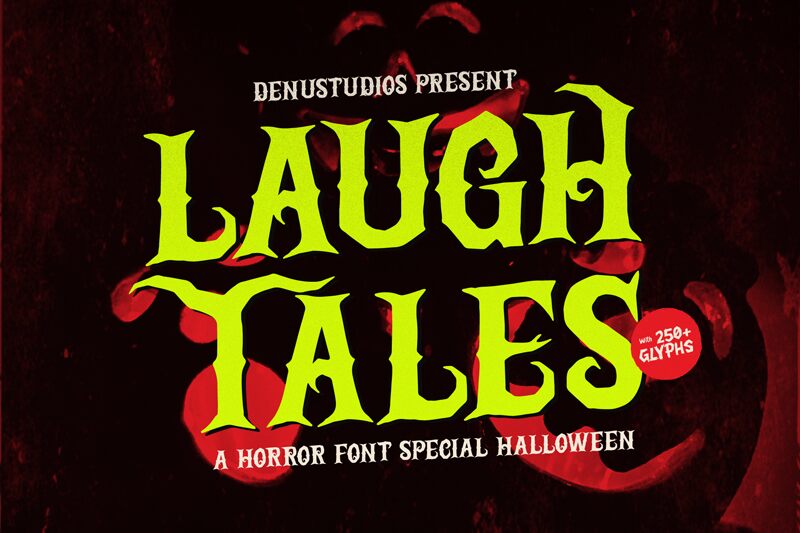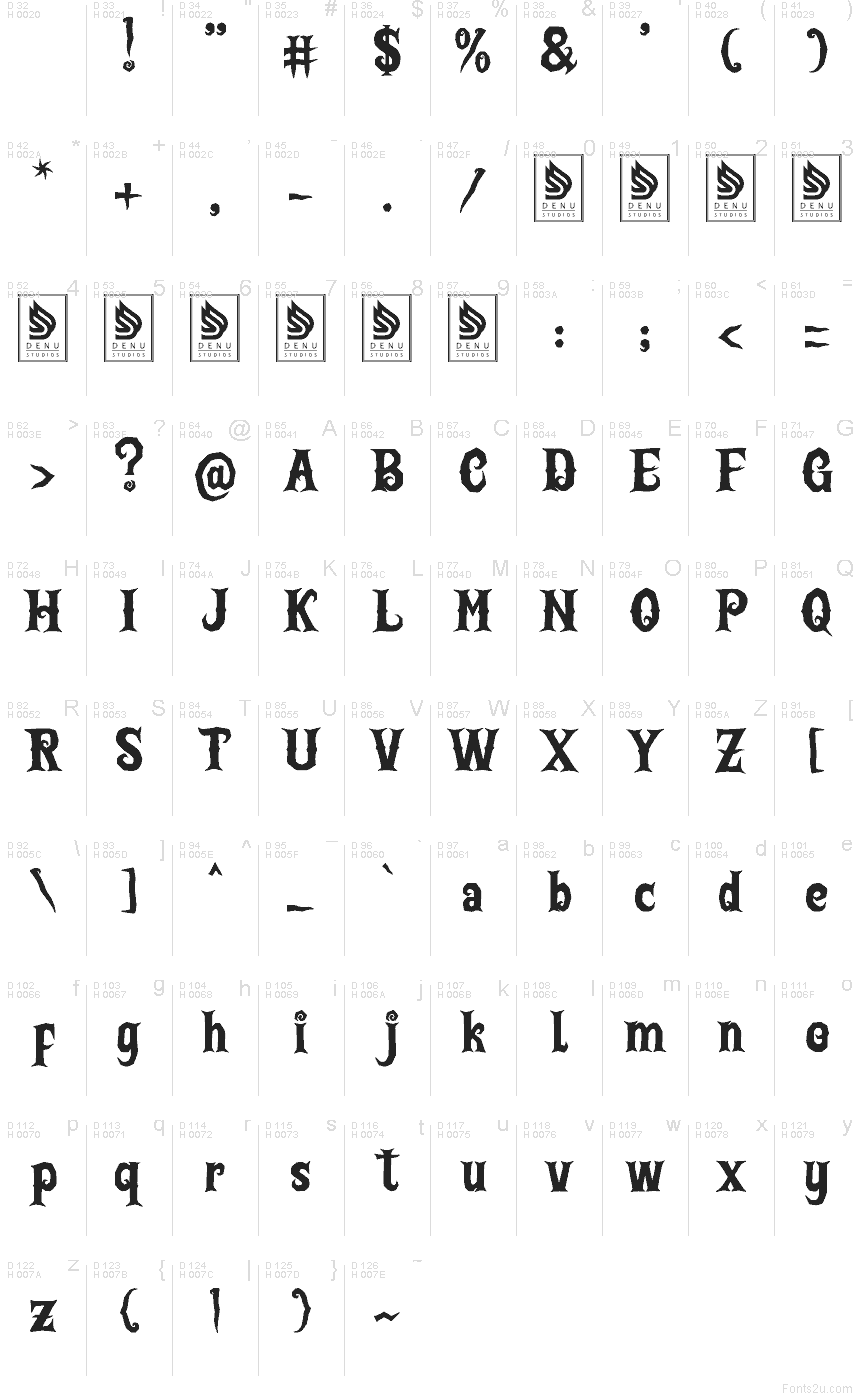
Laugh Tales de Denustudios es una tipografía Blackletter gratuita para Halloween con un aire gótico de cuento. Sus letras se definen por puntas afiladas y cornudas junto con formas medievales robustas, pero las curvas exageradas y los finales en gancho le aportan un toque divertido en lugar de solemne, dándole esa sensación traviesa de fogata.
Encaja perfectamente en carteles de eventos de terror, portadas de libros espeluznantes, embalajes temáticos, invitaciones a fiestas y títulos cortos estilo logotipo que requieren una fuente gratuita con un punto de folklore y amenaza. Gracias a que sus formas son compactas pero dramáticas, funciona especialmente bien para titulares, portadas y palabras destacadas que necesitan ese tono de leyenda antigua sin resultar rígidas.